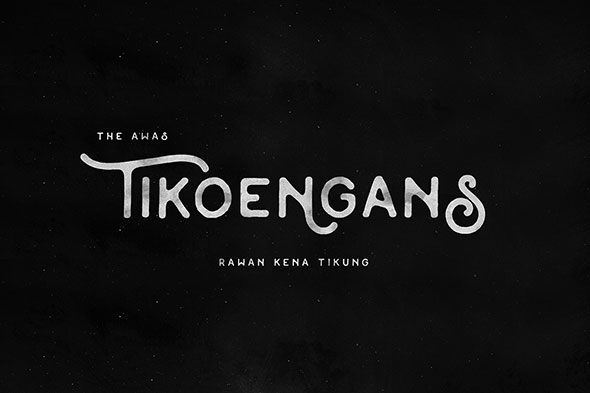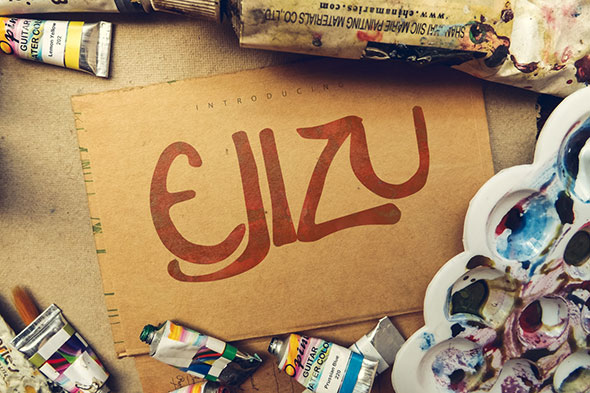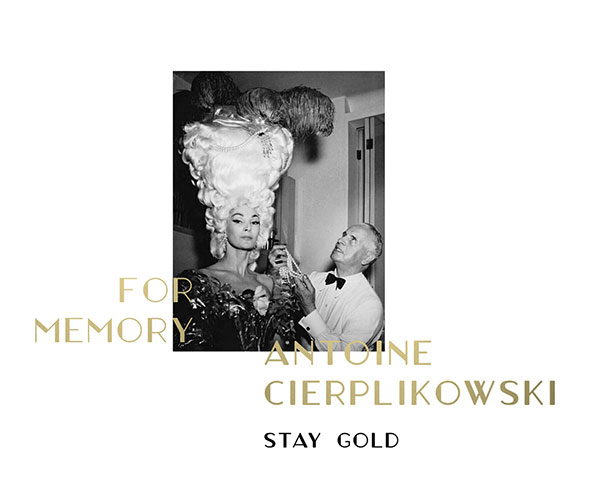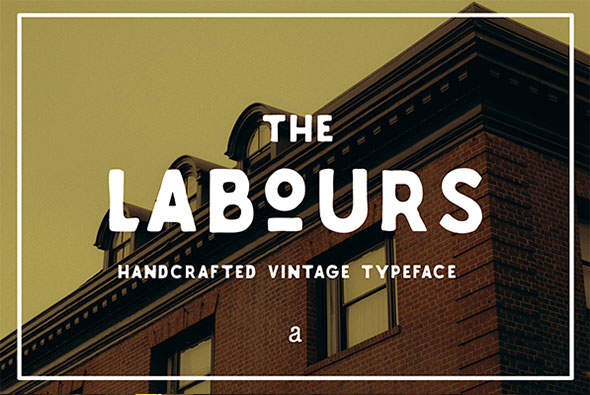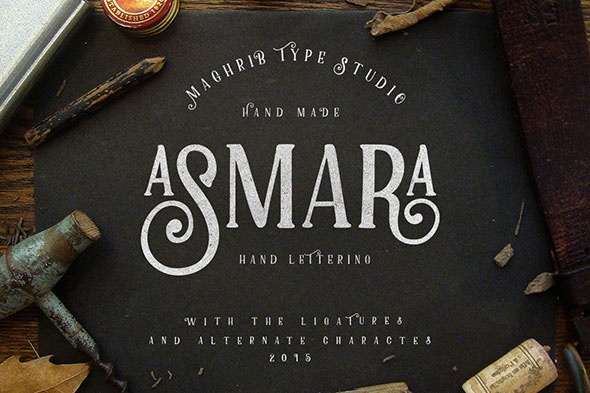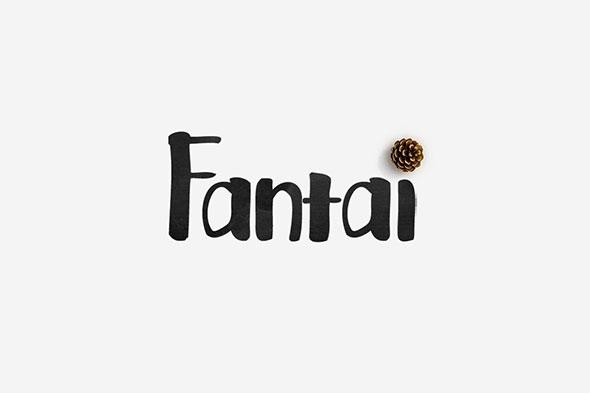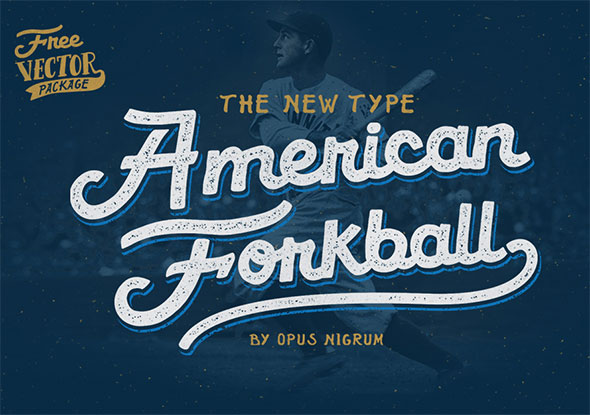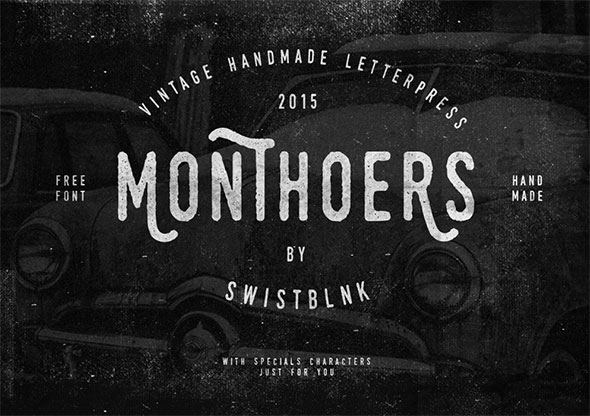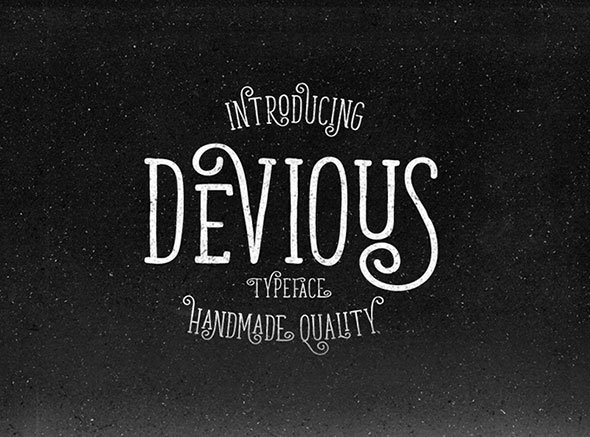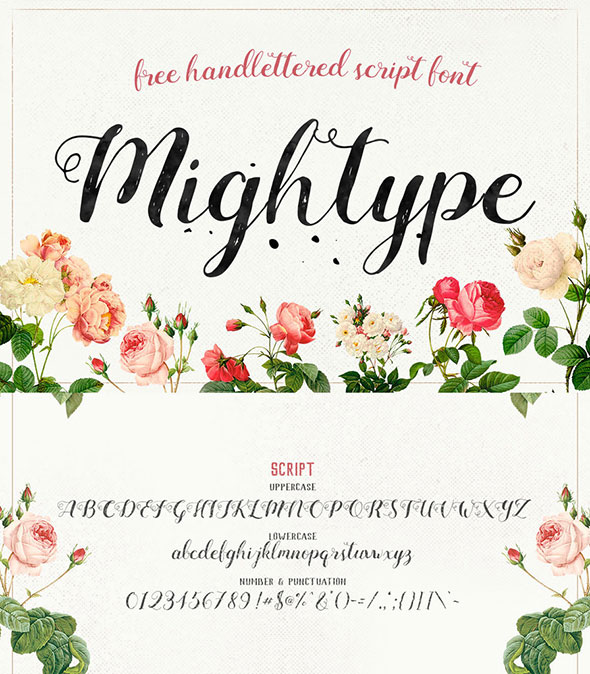
Бесплатные шрифты для заголовков и больших надписей
Сегодня мы собрали подборку бесплатных шрифтов для крутых надписей и заголовков. Ниже вы найдете самые разные начертания, которые подойдут для неограниченного списка тематик. Здесь много рукописных, изящных и стильных шрифтов, а также модных начертаний с протертостями. Выбирайте!
Pelmeshka — Free Font
Neament Free Font
Debby Free Font
Devious Typeface
Talisman Free
Michelle – Free Handmade Script
Mightype Free Handlettered Script Font
FREE FONT: FOXHOLE HAND DRAWN
PARABOLA FREE FONT
Moabhoers Free Font
Ejizu Free Marker Typeface
Beautiful Friday Typeface
.Antoine — 5 weights — Free Font
Labours Handcrafted Typeface
Asmara Typeface
Fantai Font
Maeninaja Typeface
American Forkball Font
Monthoers Free Font
Brayden Family Typefaces